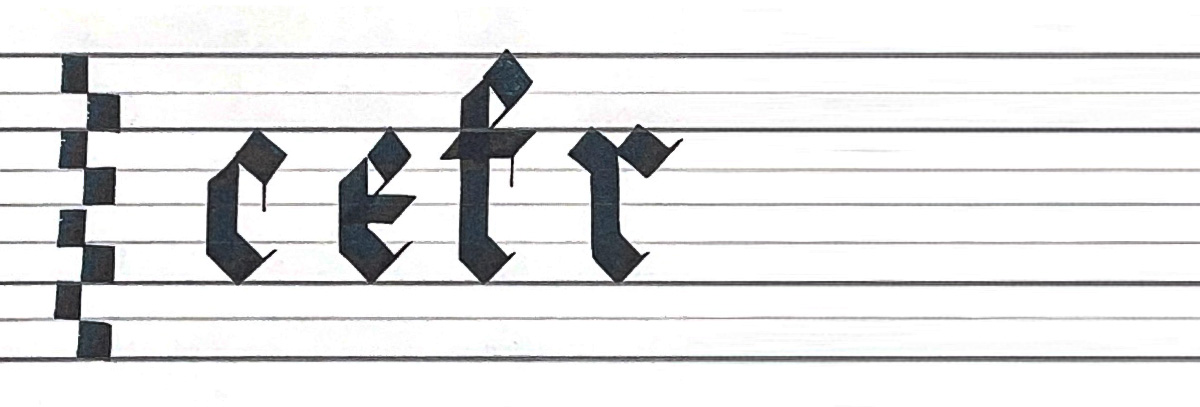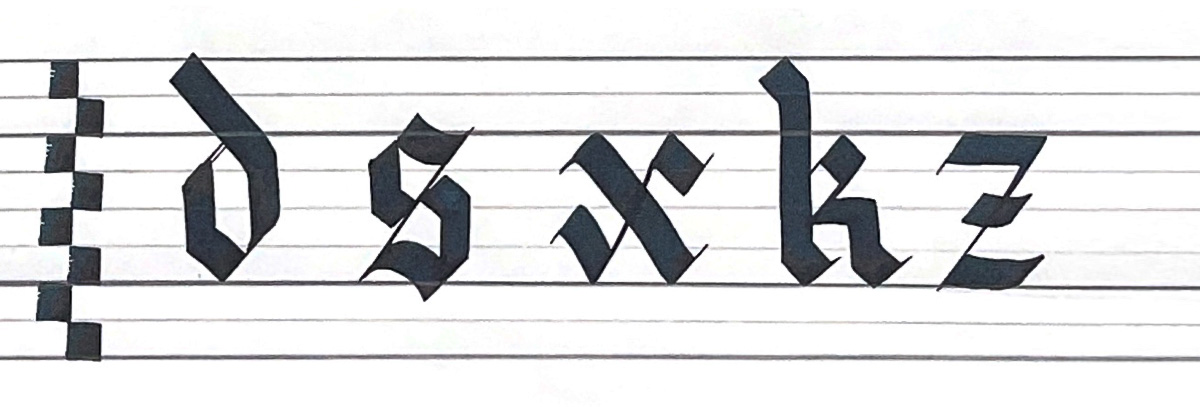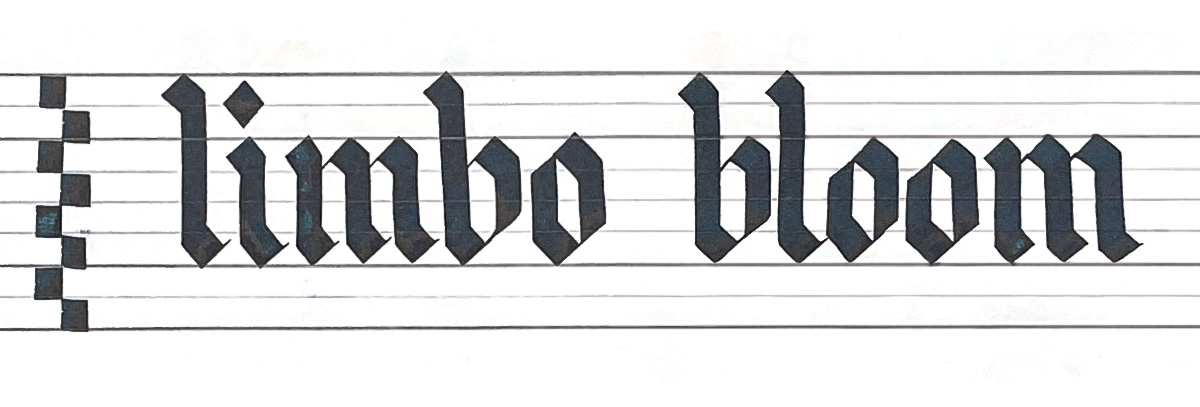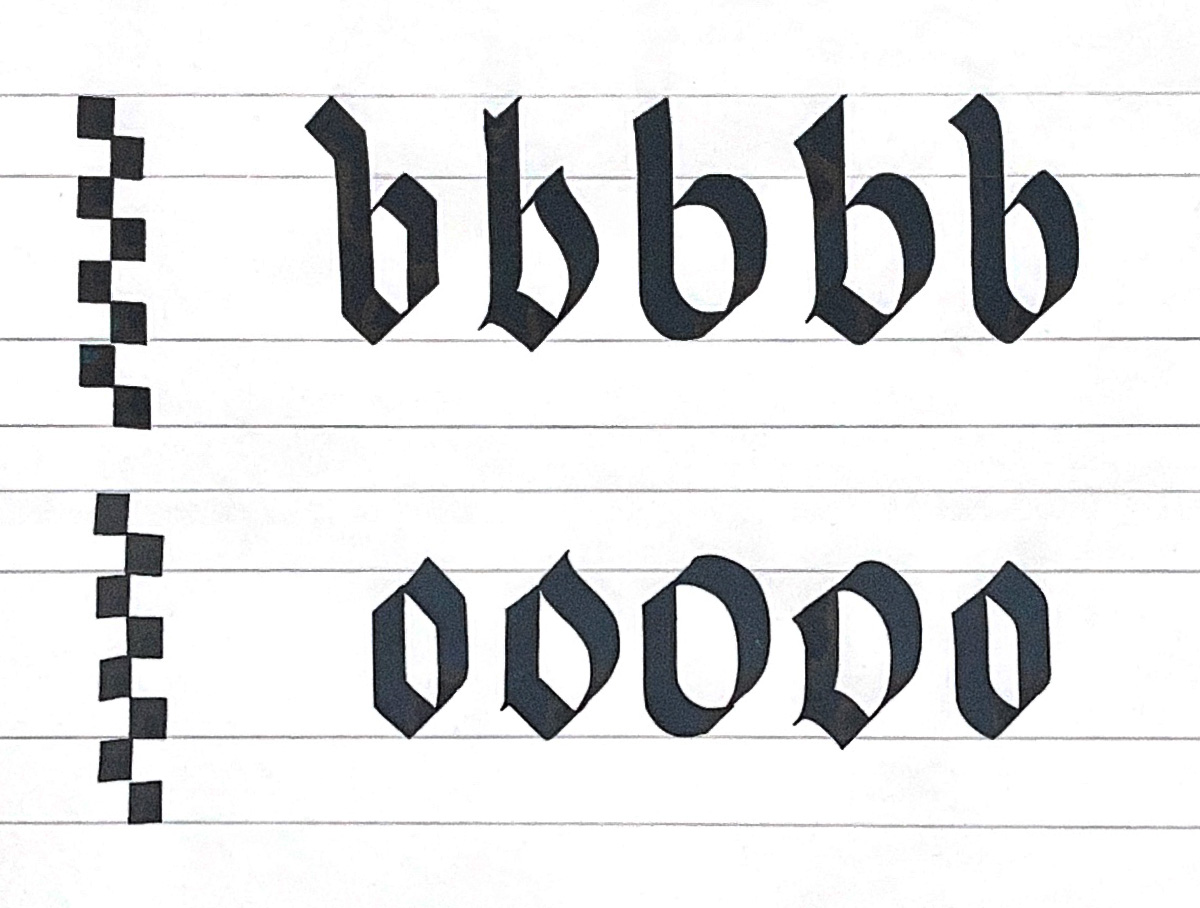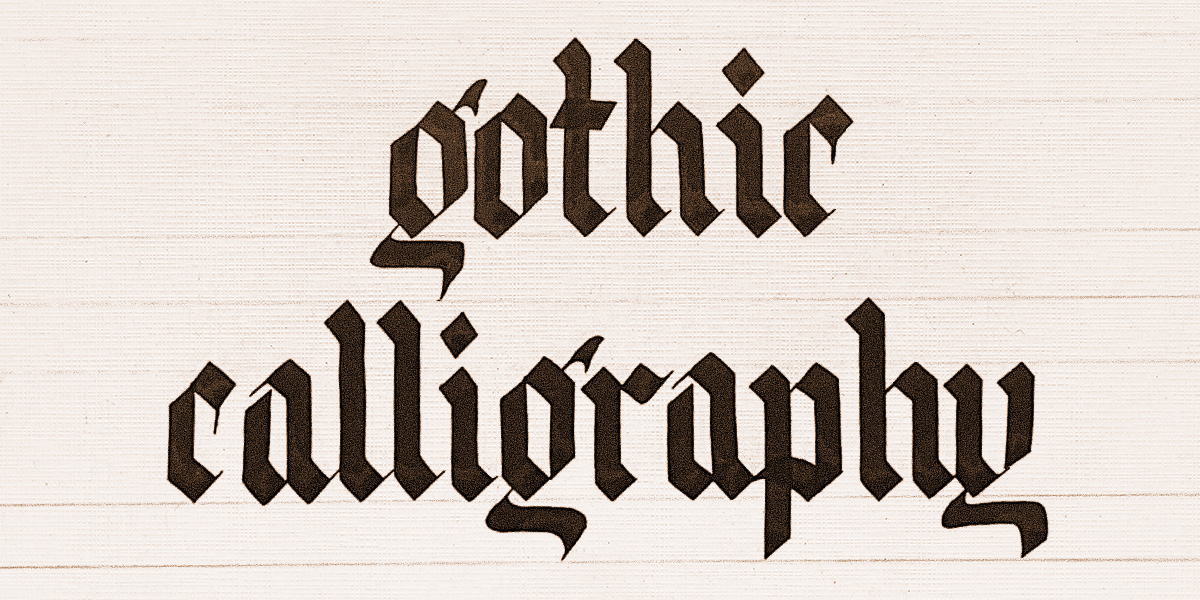
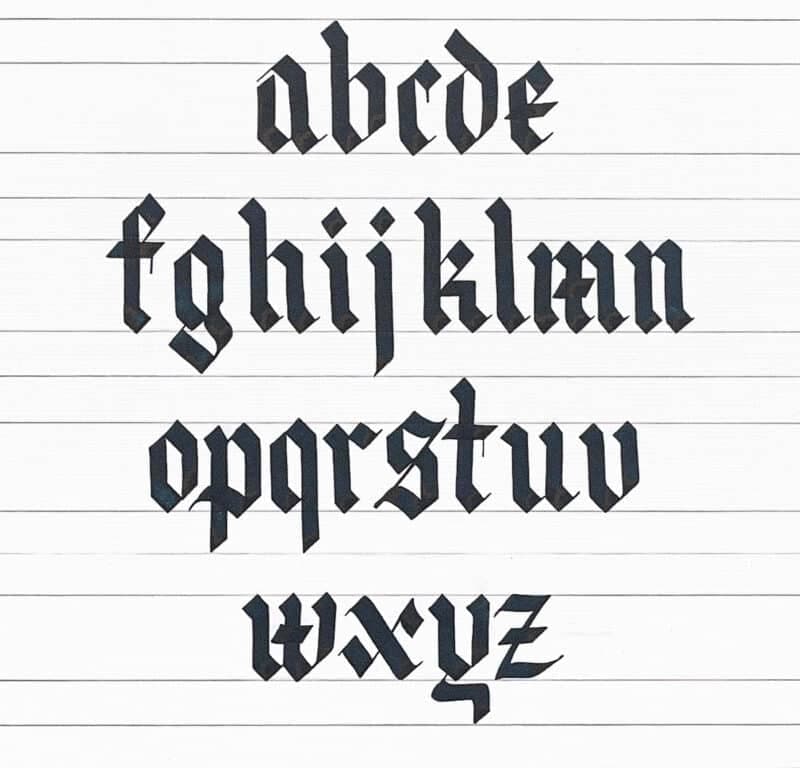
בקליגרפיה גותית צורת האות נוצרת מצורת הכלי שכותב אותה.
במקרה של אותיות גותיות, האפקט המתקבל הוא דרמטי, עוצמתי.
דרמטי, מאיים, אסתטי, דתי, מהפנט, יפה.
ככה אני רואה את הכתב הגותי. כתב שהתפתח מראשית הדפוס, מכתבי דת של הכנסייה, ועבר גלגולים שונים דרך כתבי יד אישיים, סגנונות עיצוביים שונים לאורך השנים, עיתונים ומכתבים, ועד קעקועים ולוגואים. אותי הוא כבש מהרגע הראשון שראיתי מישהו כותב אותו. הצורה האנכית והגבוהה של הכתב – יש בזה משהו מהפנט, סדר מופתי של אותיות שמשתלבות בצורה כמעט מושלמת זו עם זו.
גותי הוא הכינוי שניתן לסגנון אמנותי באיטליה (על שם השבטים הגותים, הברברים). הוא נחשב סגנון ״מקאברי״, גס, עוצמתי וכבד. הסגנון הופיע בארכיטקטורה בצורת קתדרלות ענקיות, גבוהות, מעוטרות בכבדות, כדי להראות את כוחה של הכנסייה ושל האלוהות אל מול האדם הקטן.
סגנון שהיה פופולרי באירופה בימי הביניים.מאופיין באותיות צפופות וקומפקטיות, ומשקל קו אחיד. שימש בדרך כלל עבור טקסטים דתיים, ספרי קודש ומזמורים.
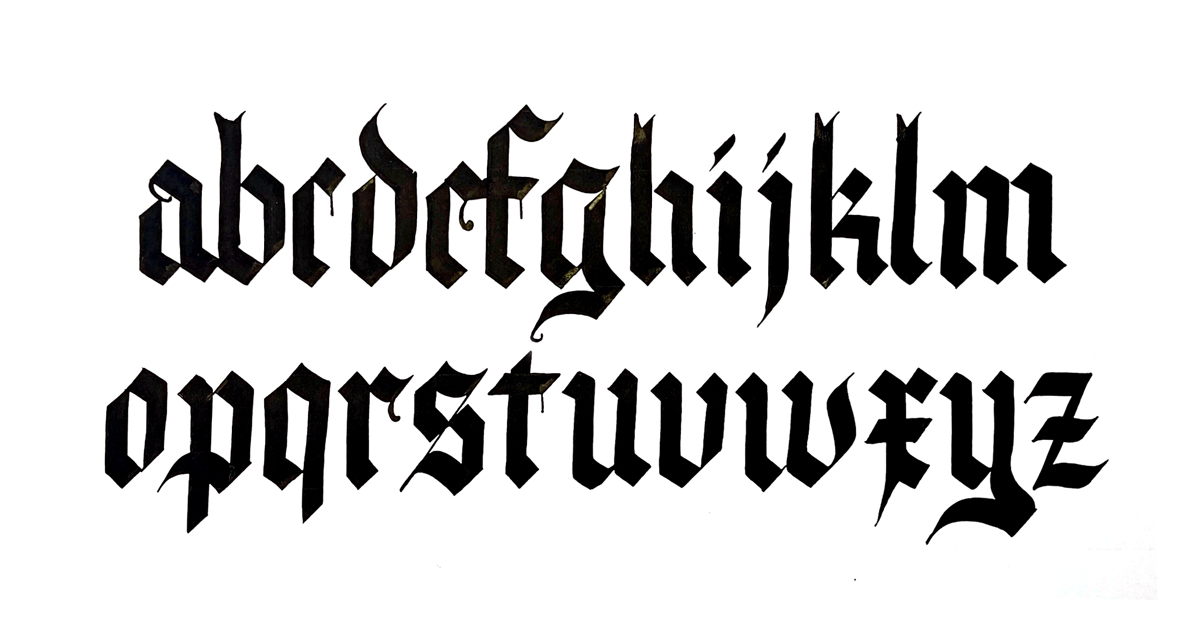
סגנון שמקורו במאה ה-16 בגרמניה. מאופיין בקווים חדים וזוויתיים ובתנועות המודגשות שלו. היה בשימוש נרחב לחומרים מודפסים, כולל ספרים ועיתונים, עד שנאסר על ידי המפלגה הנאצית בשנות ה-40.
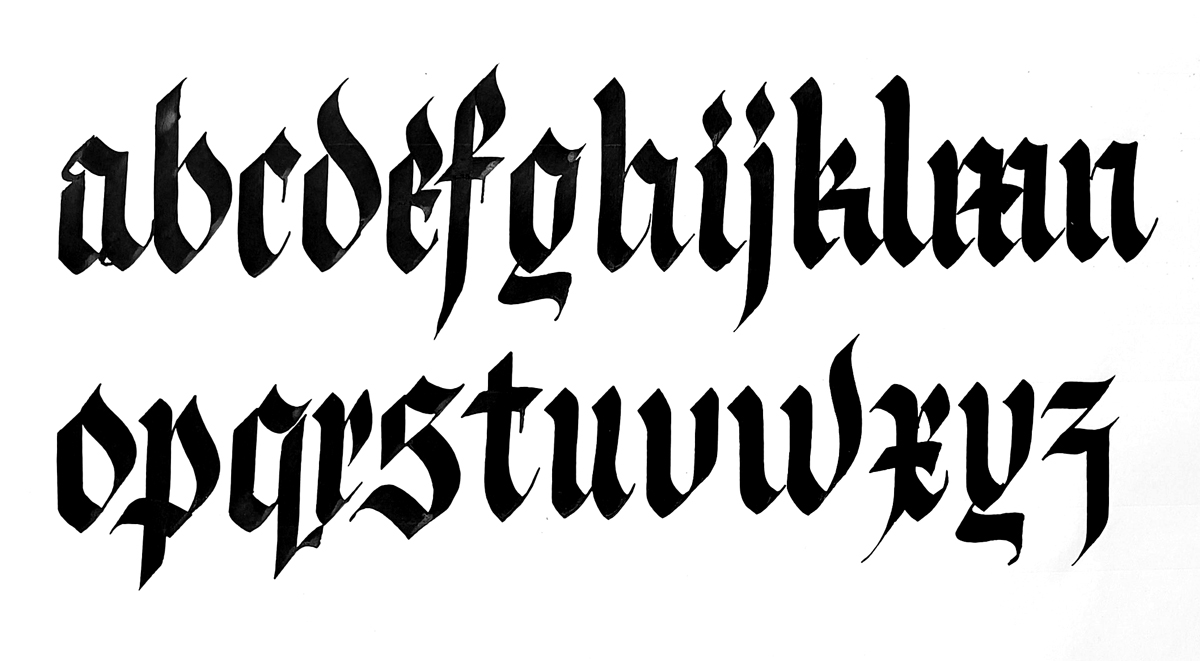
ידוע גם בשם Schwabacher-Fraktur או Cursive, הוא סגנון המשלב אלמנטים של Fraktur ו-Cursiva. הוא מאופיין במראה זורם, הדומה ל-Cursive ובהבדלים בעובי הקו, אך כולל גם אלמנטים חדים וזוויתיים הדומים לפראקטור. היה נפוץ בעיקר לכתב יד ולהתכתבות אישית.
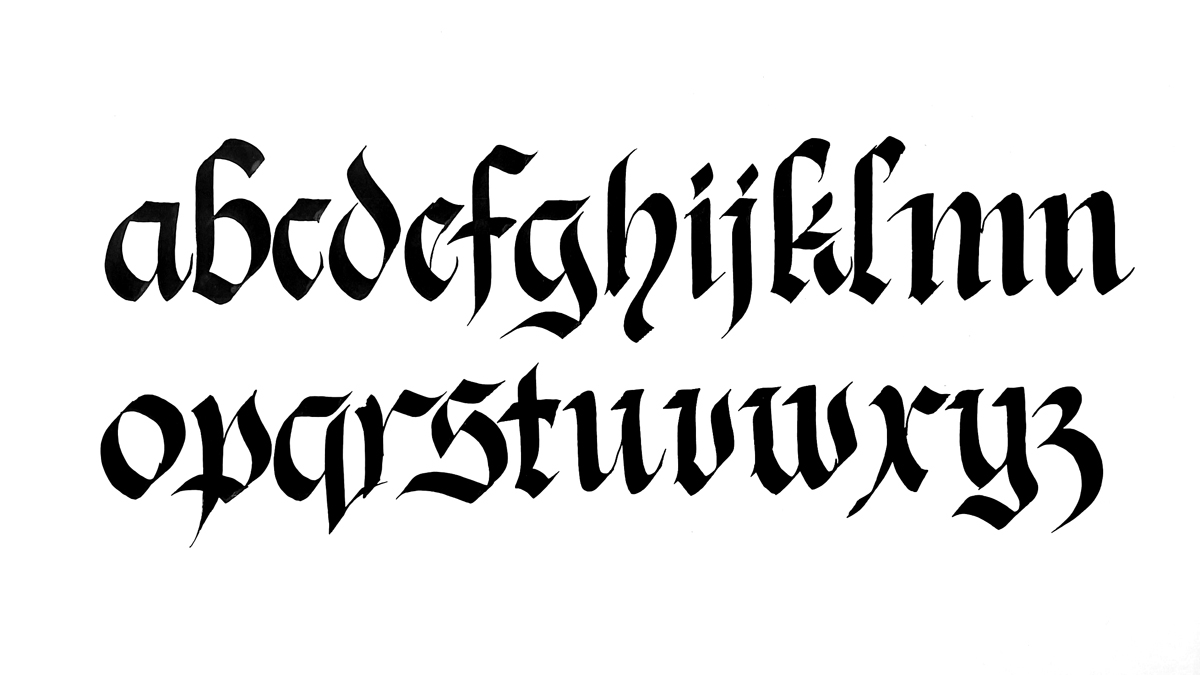
סגנון שמקורו במאה ה-15 בגרמניה. מאופיין במראה מעוגל וזורם ובשינויים בעובי הקו. שימש בעיקר לחומרים מודפסים, כולל ספרים ועיתונים, עד שהוחלף בפראקטור במאה ה-16.
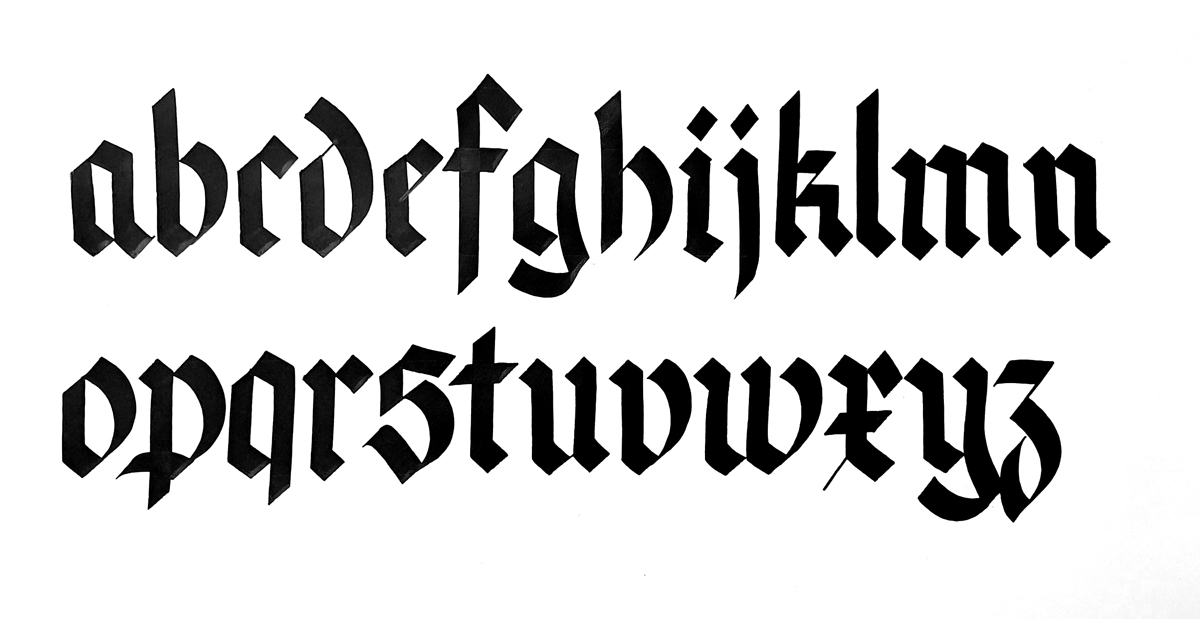
כנסו לכאן כדי לראות איך שוואבכר נכתב.
*כל חמשת הסגנונות הם שילוב או התפתחות אחד של השני בהתאם לזמן, לשימוש העיקרי, ולאזור גיאוגרפי. יש ביניהם דמיון רב, וחלק מהאותיות שונות, אך הבסיס הוא אותו בסיס.
השוואה בין סגנונות שונים של האותיות הגותיות
במדריך זה נלמד את אותיות ה-lowercase
לכתיבת קליגרפיה גותית (בכל שפה) יש שני מאפיינים בולטים: זווית הכתיבה, ואופן החזקת העט.
המאפיין הראשי בקליגרפיה הוא שצורת האות נוצרת מצורת הכלי שכותב אותה. עט עם קצה רחב ייצור אות רחבה, עט מברשת ייצור אות אקספרסיבית בהתאם ללחץ שנפעיל.
לכל סגנון יש זווית ייחודית לו – זה משתנה שאנחנו יכולים לקבוע. אבל ברגע שהחלטנו, רצוי להישאר בזווית הזאת כדי לייצר אותיות סיסטמטיות וזהות. בקליגרפיה גותית נכתוב בזווית של 45 מעלות.
זווית הכתיבה. בין 40-45 מעלות.
צורת הכתיבה היא חשובה מכיוון שהיא תקבע את הניראות היציבה והקונסיסטיות של האותיות, ותעזור לנו להישאר בזווית הנכונה.
התנועה תהיה מהמרפק והכתף ולא מפרק כף היד. פרק כף היד נעול במקומו בזמן שאנחנו מחזיקים את העט.
פרק כף היד סטטי ורק מחזיק את העט. התנועה מגיעה מהכתףהגריד הטיפוגרפי הראשי מורכב מ-5 שורות: Ascender (קו רשת עליון, עבור אותיות העולה מעל הקו: h, l, d, b), Descender (קו הרשת התחתון, עבור אותיות שנכנסות מתחת לקו: p, q, g, y), X-hight ( גובה האותיות), קו הבסיס ו-Cap Hight (גובה ה-uppercase).
אתחיל מהמרחק בין קו הבסיס לגובה x ואמדוד פי 4** מהרוחב של קצה מכשיר הכתיבה (במקרה זה – Pilot Parallel 6mm). המרחק בין גובה x ל-asceneder יהיה כפול מרוחב כלי הכתיבה. ואותו הדבר לגבי המרחק בין קו הבסיס ל-desender.
*עבור מדריך זה לא נשתמש ב-Cap hight.
**מידה זו תמיד ניתנת לשינוי. זה ייצור אותיות מוארכות או אותיות מקוצרות (ניסוי טיפוגרפי נחמד).
נקרא למשיכות הקו הבסיסיות של האותיות בשמות חלקי פרחים: ניצן, גבעול ושורש.
הניצן לוקח את הרבע העליון של גובה ה-x, הגבעול לוקח בדרך כלל את 2 הרבעים האמצעיים והשורש לוקח את הרבע הרביעי של המרחק בין הבסיס לגובה x.
כולם בזווית 45 מעלות של כלי הכתיבה.
ניצן גבעול ושורש
כעת נחבר בין שלושת החלקים:
עכשיו יש לנו את האות i. זהו הבסיס של האותיות בקליגרפיה גותית.
על ידי חיבור 2 אותיות i, נקבל n. לאחר סיום i, אחזור לתחילת הגבעול ואדחוף את העט מעט לימין למעלה כך שיווצר חלל לבן בין שני ה-i. ואז אני מצייר עוד ניצן, גבעול ושורש. יש לנו n!!! חזרה על האות i תיצור את האות m.
הקווים הבסיסיים וחיבורים לכדי יצירת אותיות של קליגרפיה גותית
כעת נוכל ליצור אותיות נוספות עם אותו מבנה בסיסי וגובה: o, u, v, w, a.
שימו לב איך עבור חלק מהאותיות אנו משתמשים בכל שלושת חלקי הפרחים ועבור חלק אנו משתמשים רק בגבעול ובניצן או רק בגבעול ובשורש.
a o u v w
עבור קבוצת האותיות הבאה (b, h, l, p, q, t, y, g, j) – אותיות שעולות מגובה השורה או יורדות ממנה,
נאריך את הגבעולים מה-Ascender או ל-descender. גם כאן – הניצן יהיה ברבע הראשון העליון של הגריד והשורש יהיה ברבע האחרון. הגבעול יהיה בחלקים העיקריים שבין הניצן לשורש.
b h l p q t j
* האותיות g ו-y הן ייחודיות וניתן לכתוב אותן בשתי דרכים:
נסו עכשיו לכתוב משהו, הנה כמה מילים שתוכל להתאמן עליהן:
bloom, limbo, onion, wow, no, numb, moon, bowl, low, hub
limbo, bloom
לקבוצת האותיות הבאה, c, r, e, f יש קווים דומים מאוד אך עם שינויים עדינים בכל אחד מהם:ֿ
c e f r
לאות c אין ניצן. הגבעול מתחיל מהרבע השני מסתיים בשורש. אליהם מוסיפים ניצן קטן (כמעט כמו שאנחנו עומדים לכתוב את האות n אבל ללא גזע ושורש).
האות e מתחילה כמו האות c, אבל אנחנו סוגרים את הניצן ומחברים אותו לגזע באותה זווית של כלי הכתיבה. בדרך כלל נוסיף קו חוצה באמצע הגבעול.